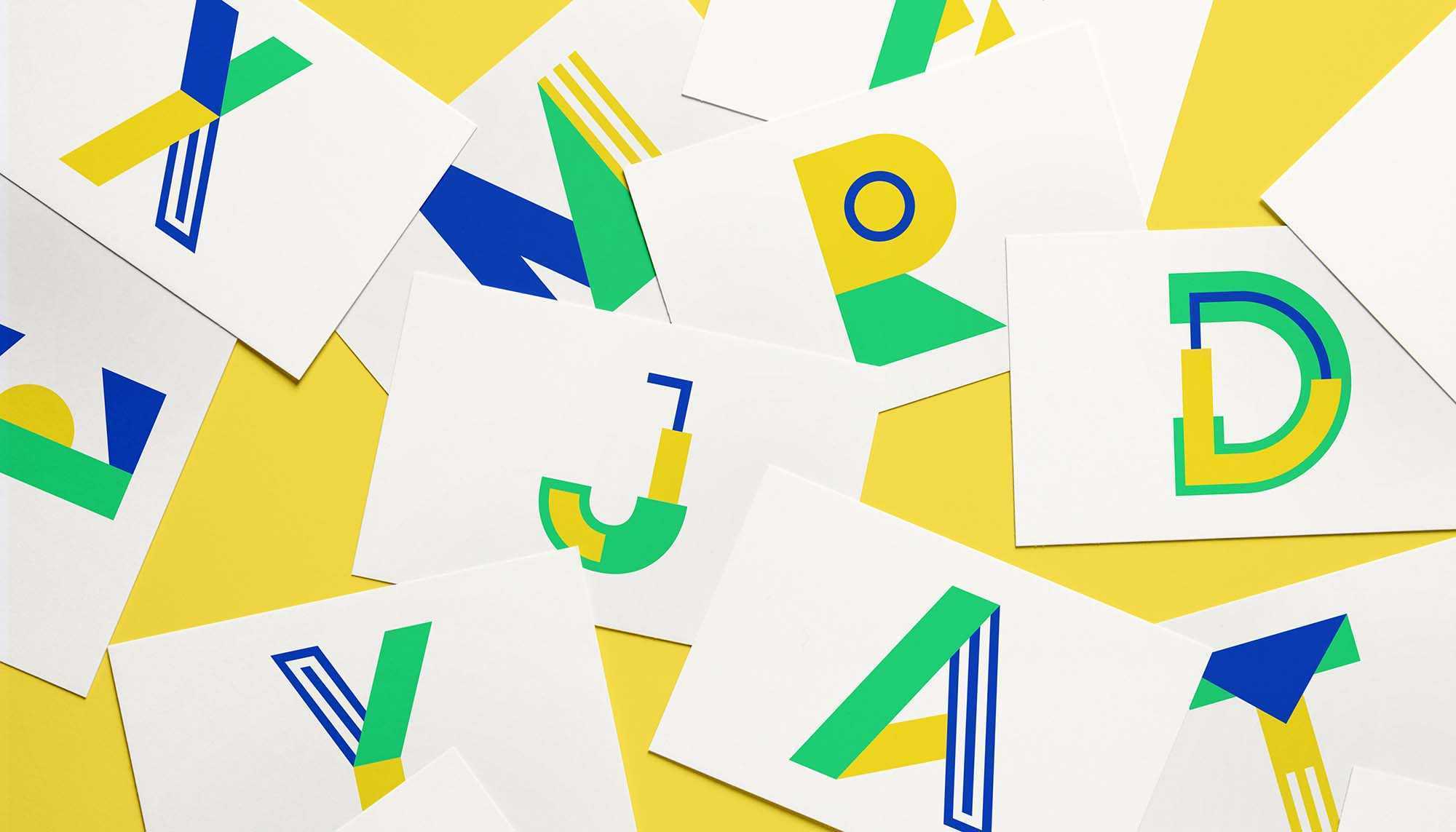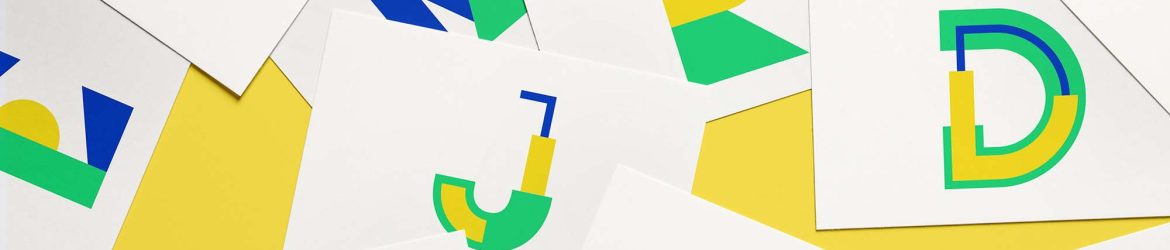
A Metra é uma fonte tipo gráfica que destaca-se por seu design vibrante e original. Desenhada por Nelly Boyanova, uma talentosa designer gráfica e ilustradora de Copenhagen, Dinamarca, esta fonte tem um toque divertido e moderno. A Metra é perfeita para designers que procuram adicionar um toque de diversão e criatividade aos seus projetos. Suas formas geométricas são combinadas de maneira incrivelmente bela e armoniosa, tanto para letras quanto para números. A Metra está disponível no formato vetor, permitindo que você crie palavras e frases conforme desejar, usando programas de edição de vetores. Seja para um projeto de design, ou seja apenas um toque de diversão para seus projetos pessoais, a Metra é uma escolha perfeita.